在品牌传播过程中,字体的设计不仅要体现创意和美感,更重要的是体现品牌的精神和内涵、确保品牌形象准确明了地传达给受众。活泼灵动风格的字体更容易抓住看客的眼球,令人印象深刻,甚至会去寻找图片上的字体。说了这么多不如一起看下到底是哪些字体具有如此能力吧?
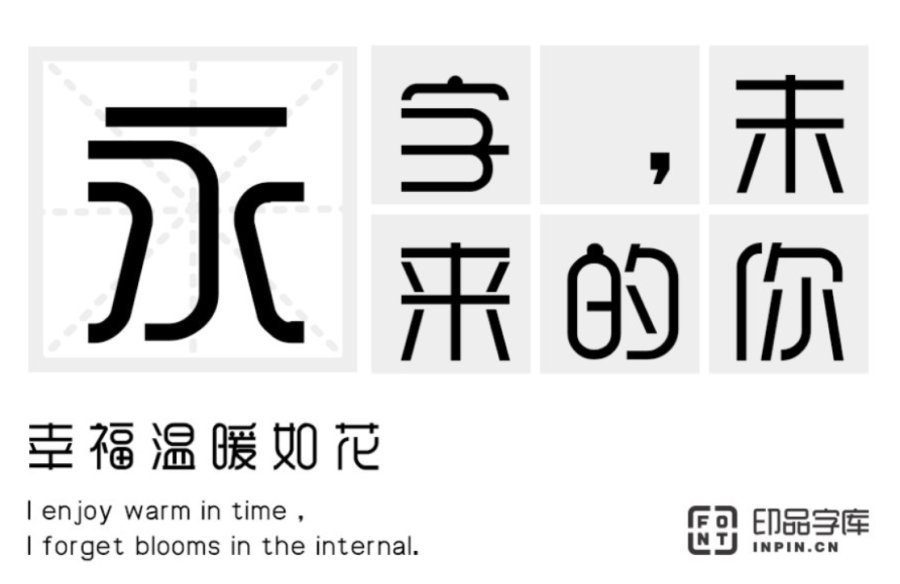
印品雅圆体:所谓圆体是英文书法的延伸及日常化,较为随意。雅圆体,对弧形做了内凹外凸的处理,使得笔画更加居中圆滑。表面结构匀称统一,字型做了细致比例的调整,整体观来更加珠圆玉润。加强装饰感的同时,多添了一分俏皮可爱。
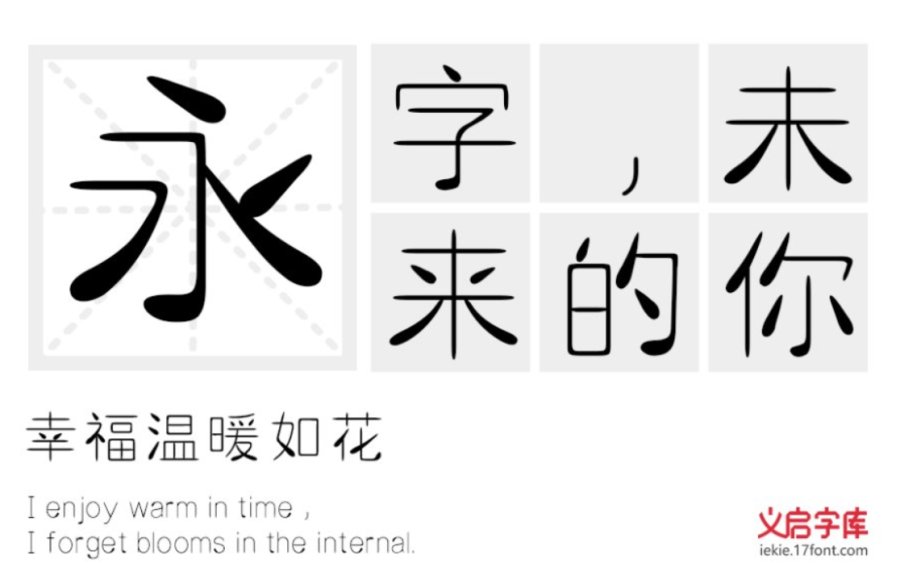
小蝌蚪找妈妈:这款字体在起笔收笔处加粗线条,就像小蝌蚪游走在字里行间。字形粗中有细,趣味十足、自然灵动。适用于封面设计、广告设计、动漫、影视、社交网络的个性或用字等领域。
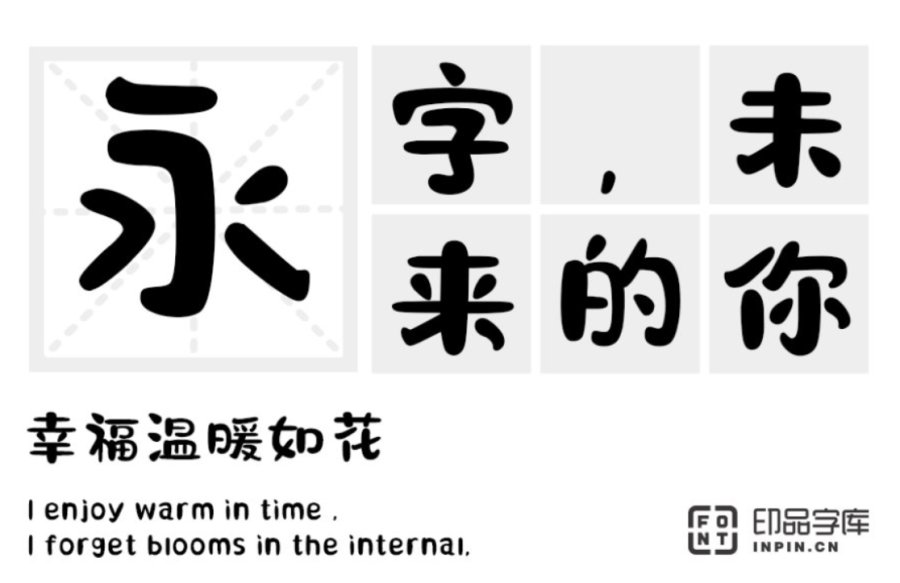
印品囧囧体:这是一款恣意洒脱、随性又妙趣横生的萌宠体,浑圆流畅。“人在囧途寻知己,久然难现实未果。”体现出随心洒脱的风格,诙谐幽默。适用于包装设计、动漫、影视、广告、游戏等领域。